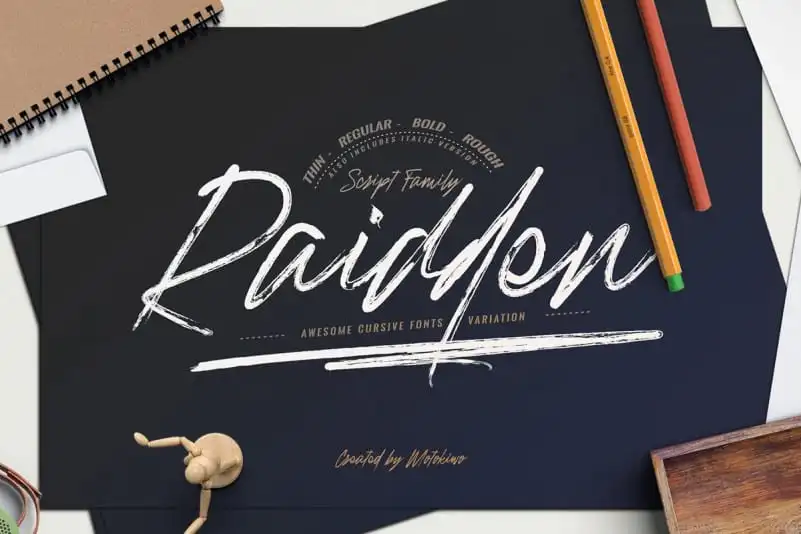
Raidden Script Font Family – Download Grátis
A Raidden Script Font Family é uma família moderna de fontes script que oferece um novo equilíbrio entre a frescura e a elegância na tipografia atual. Inspirada no estilo de calligrafia à mão, essa família apresenta caracteres decorativos e uma linha base dançante. Ela foi criada pelo designer Motokiwo para fornecer flexibilidade ao usar o Raidden em diversos projetos com estilos variados. Esta fonte cursive inclui três pesos limpos que permitem um contraste interessante, além de uma versão mais suave e irregular. As variações proporcionam facilidade na utilização do Raidden para diferentes tipos de projeto e estilo. Seja o modo elegante da tipografia limpa ou a versão áurea e irregular, ambas se destacam melhor quando combinadas com ligaduras e ganchos. A Raidden Script é uma fonte perfeita para quem busca um equilíbrio entre modernidade e sofisticação. A família oferece opções que vão do elegante ao esplêndido, permitindo a criação de design único e autêntico em qualquer projeto.